「ネームロゴ」にぴったりの日本語フリーフォント
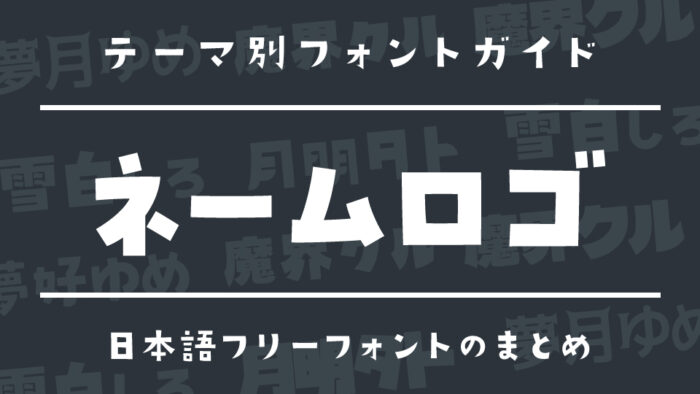
今回は、印象的な「ネームロゴ」にぴったりな日本語フリーフォントをご紹介します。
Vtuber名やクリエイター名、アーティスト名などを個性豊かに表現する“ネームロゴ”は、第一印象を左右する大切なデザイン要素です。
今回は、VtuberやSNSプロフィール、YouTubeのチャンネルロゴなどにも使いやすい、印象に残る日本語フリーフォントをピックアップしました。自分らしさをフォントで表現したい方にぴったりの個性豊かなフォントばかりです。
自分だけの“名前ロゴ”が作れる!ネームロゴ向け日本語フリーフォント
本記事では、ネームロゴにぴったりのフォントをご紹介します。以下のサンプル画像のように「かわいい雰囲気」「かっこいい雰囲気」などさまざまピックアップしています。また、1つのフォントだけではなく、フォント同士を組み合わせ使うといった方法も素敵かと思いますので、ぜひご参考にしてみてくださいね。
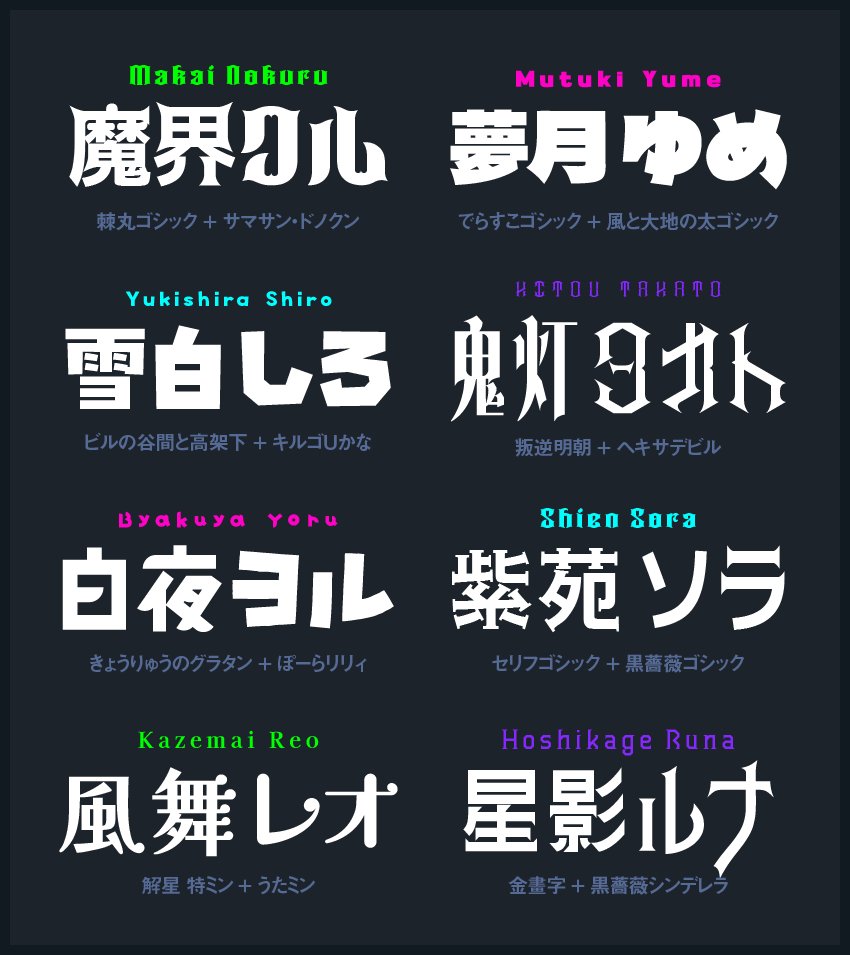
棘丸ゴシック
棘丸ゴシックフォントは、ゴシック体の文字をベースに、文字先端にトゲのような装飾と、丸のモチーフが組み合わせって作られたデザインフォントです。
高貴な雰囲気を作りたいネームロゴにぴったりです。
源暎きわみゴ
源暎きわみゴフォントは、「デラゴシック」フォントをベースに、オリジナルかな文字・英数字に置き換えて制作された超極太のゴシック体フォントです。
インパクトも読みやすさも考えられているので、Youtubeチャンネルロゴなどでも活躍できるフォントです。
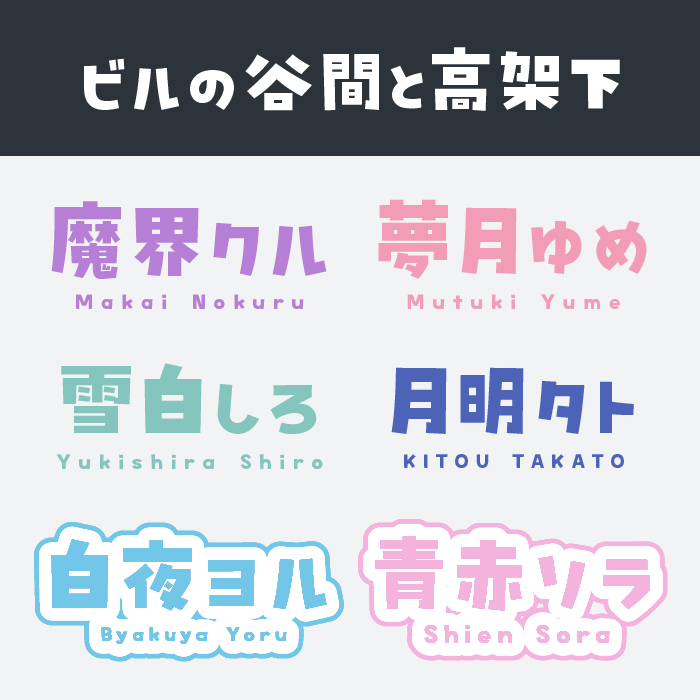
ビルの谷間と高架下フォントは、漢字とひらがな、カタカナのでこぼこ感が可愛いらしいデザインフォントです。Vtuberのネームロゴに人気のあるフォントの1つです。
叛逆明朝
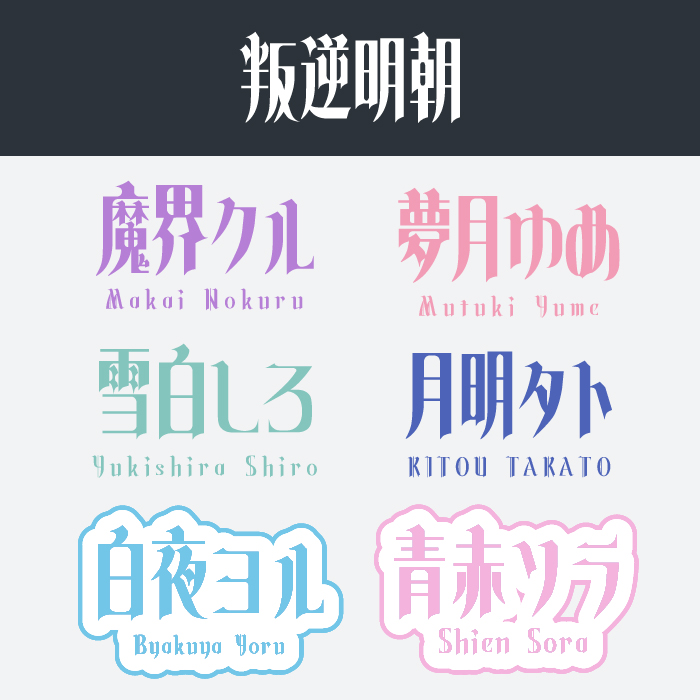
叛逆明朝(Hangyaku)フォントは、文字先端に装飾されており、エレガントな雰囲気と、ゴスロリのような雰囲気を持っている長体系フォントになっています。
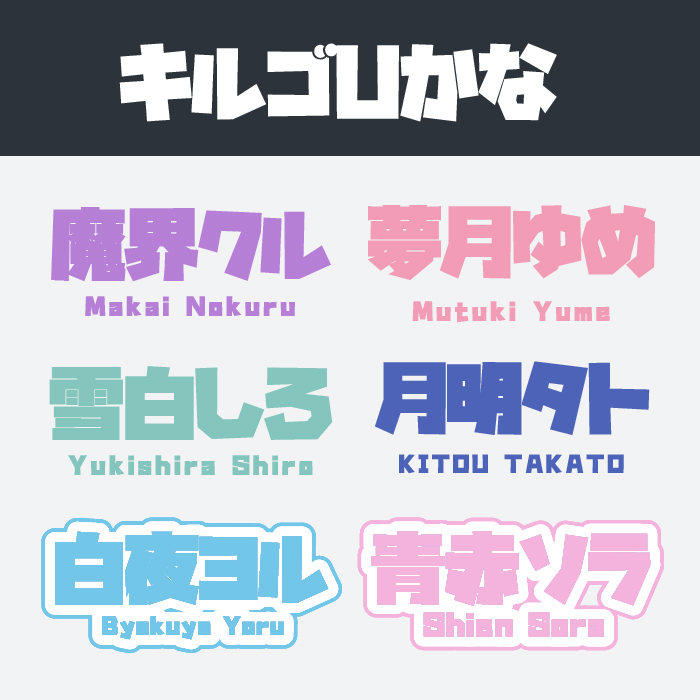
キルゴUフォントは、アニメロゴをモチーフとしているので、ゴツゴツしたフォルムがポップで元気な印象を作りたいネームロゴにぴったりなフォントです。
風と大地の太ゴシック
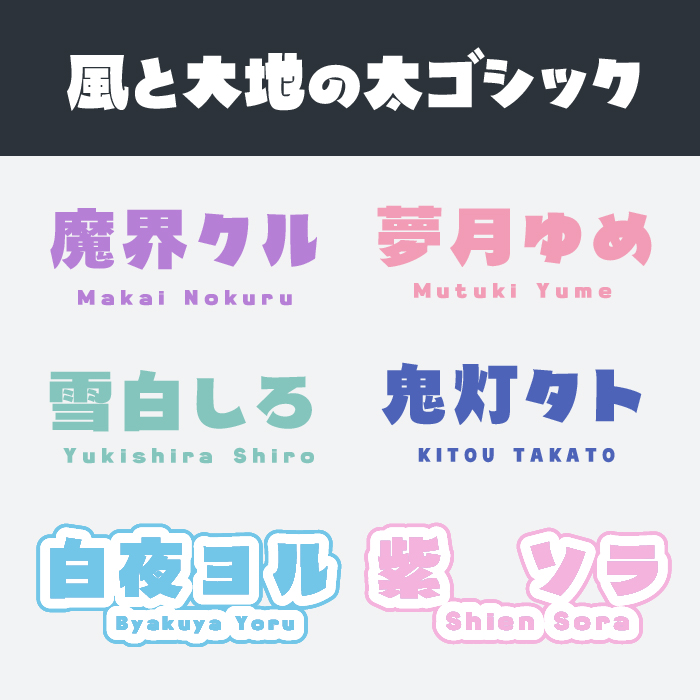
風と大地の太ゴシックフォントは、風の勢い、大地の力強さが表現されて、ポテッとしたフォルムが可愛らしいゴシック体です。インパクトがありつつ、自由な雰囲気で可愛らしいデザインのフォントです。
セリフゴシック
AFSセリフゴシックフォントは、文字先にどっしりとしたセリフ装飾が付けられているデザインゴシック体のフォントです。
解星 特ミン
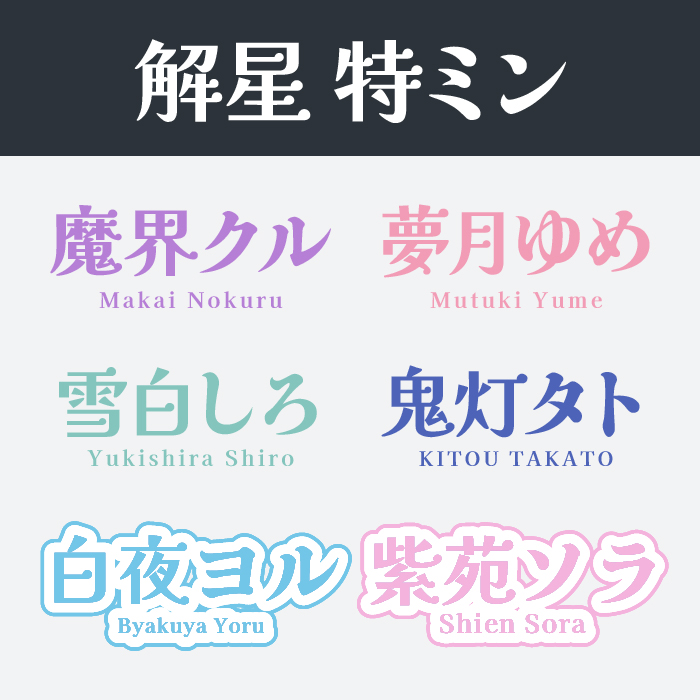
解星 特ミン(Kaisei Tokumin)フォントは、線が太く力強いかな文字と、文字先にドットの装飾が付いている可愛くてユニークな明朝体フォントです。大人っぽい可愛らしいネームロゴを作りたいときにぴったりなフォントです。
うたミン
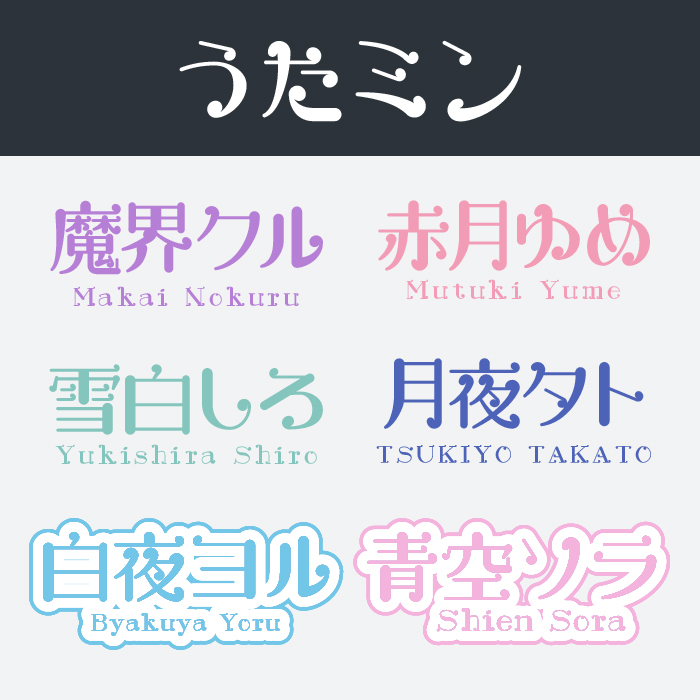
うたミンフォントは、歌う文字というコンセプトで作られてたフォントです。音符をモチーフとしているデザインがとっても可愛らしいです。
金畫字(キンカクジ)
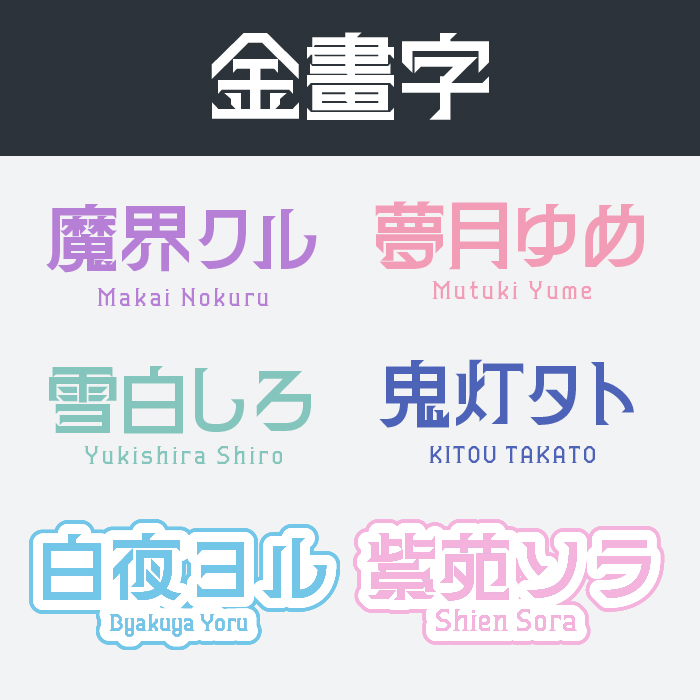
金畫字(キンカクジ)フォントは、縦・横・斜(45°)の直線を主軸にデザインを展開し、四隅やハネや点・払いの表現に直角三角形で構成されているフォントです。クールでかっこいい雰囲気を作りたいネームロゴにぴったりなフォントです。
けいなんポップ体JP
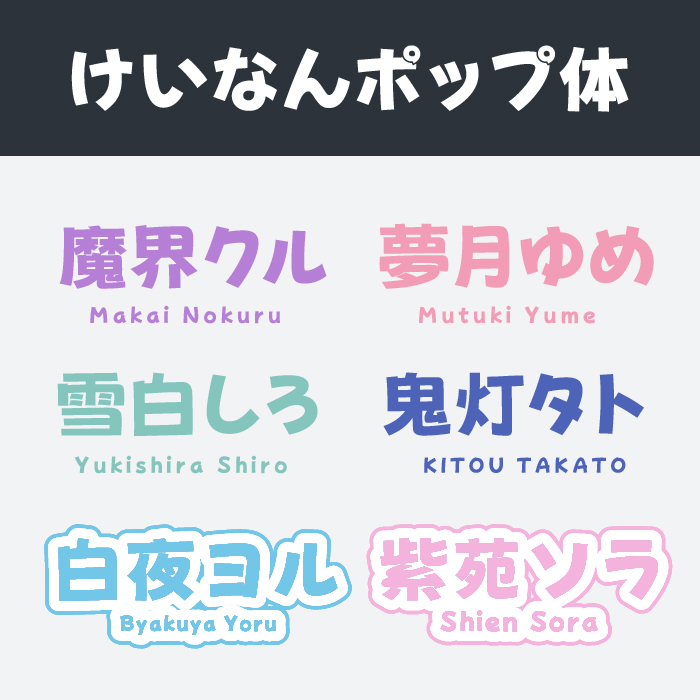
けいなんポップ体JPフォントは、手描き風のような丸みと、弾むようなリズム感が親しみやさがあり、楽しそうな雰囲気をもつ可愛らしいフォントです。
推しゴフォントは、推し活グッズ制作を目的に作られたフォントで太さもあり、遠くからの見えやすさにこだわって作られたゴシック体フォントです。漢字収録は少なめですが、自身のネームの文字が揃っていたり、かな文字だけ使ってみるなどでもおすすめです。
黒薔薇シンデレラ
黒薔薇シンデレラ&赤薔薇シンデレラフォントは、長体ゴシック体をベースに薔薇のようにトゲトゲの装飾されているユニークなデザインフォントです。ゴスロリ感な雰囲気を作りたいときにもおすすめなフォントです。
きょうりゅうのグラタン
きょうりゅうのグラタンフォントは、太めで丸みが可愛いデザインフォントです。